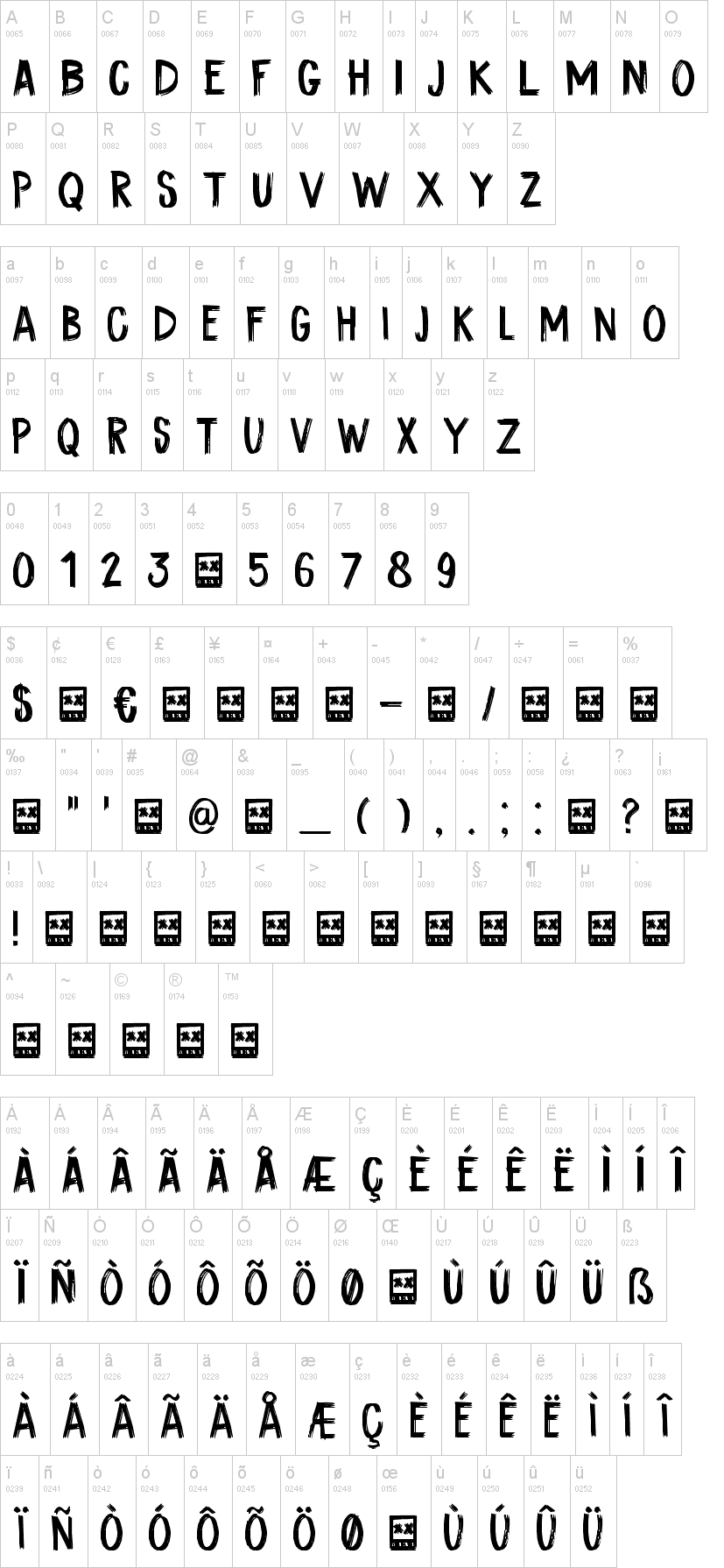
DK Coal Brush
DK Coal Brush 是一款手写风格的字体,具有浓重的笔刷笔触和粗糙的质感。该字体设计师是英国的 Hannah Smith,她灵感来自于石墨和炭,以及手写风格的艺术品和手写书信。 DK Coal Brush 字体包含了大写字母、小写字母、数字和一些标点符号。它特别适合用于设计海报、书籍封面、标志、宣传册等需要强烈个性化和手工感的设计作品。 该字体的设计和制作精细,使用起来非常方便。它是一款非常受欢迎的字体,可以在商业和个人项目中使用,也可以在许多字体网站中下载。
DK Coal Brush是一款非常不错的手写艺术字体,具有很好的视觉感,适合于文化类的宣传设计、商业类品牌的广告和产品包装设计以及个性化文字排版等较多场景。